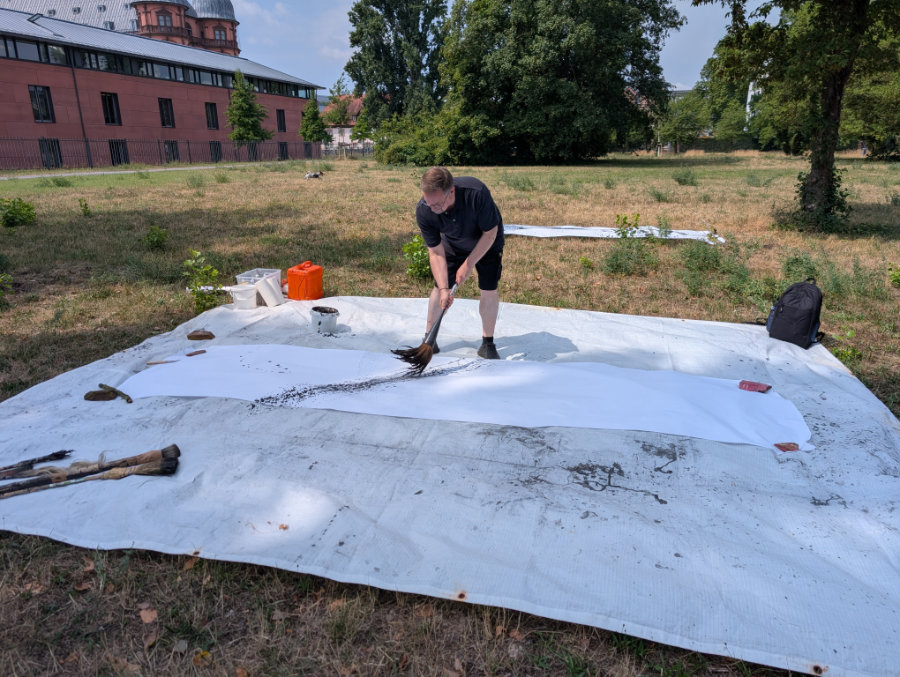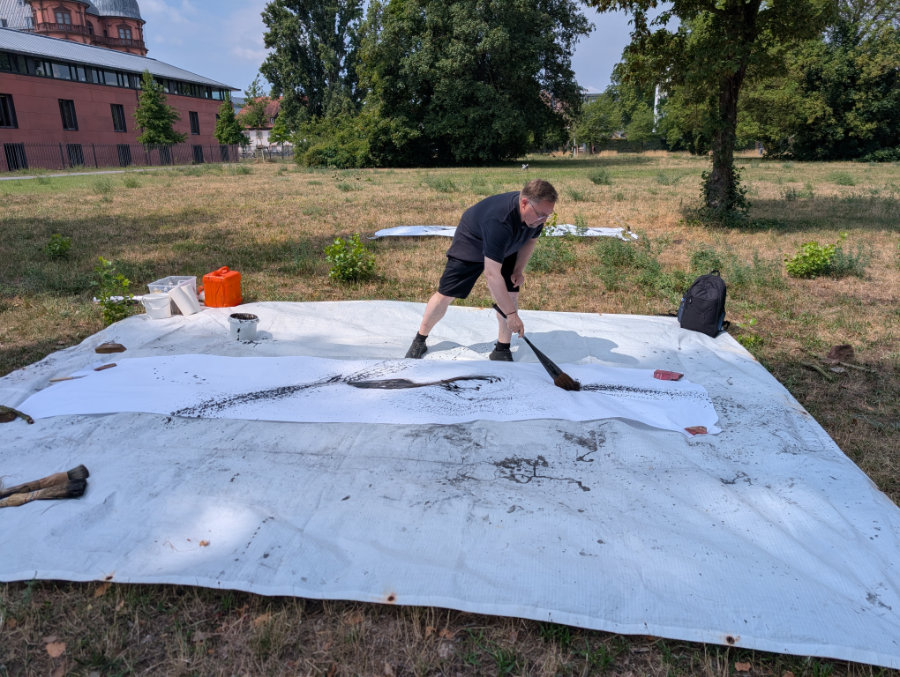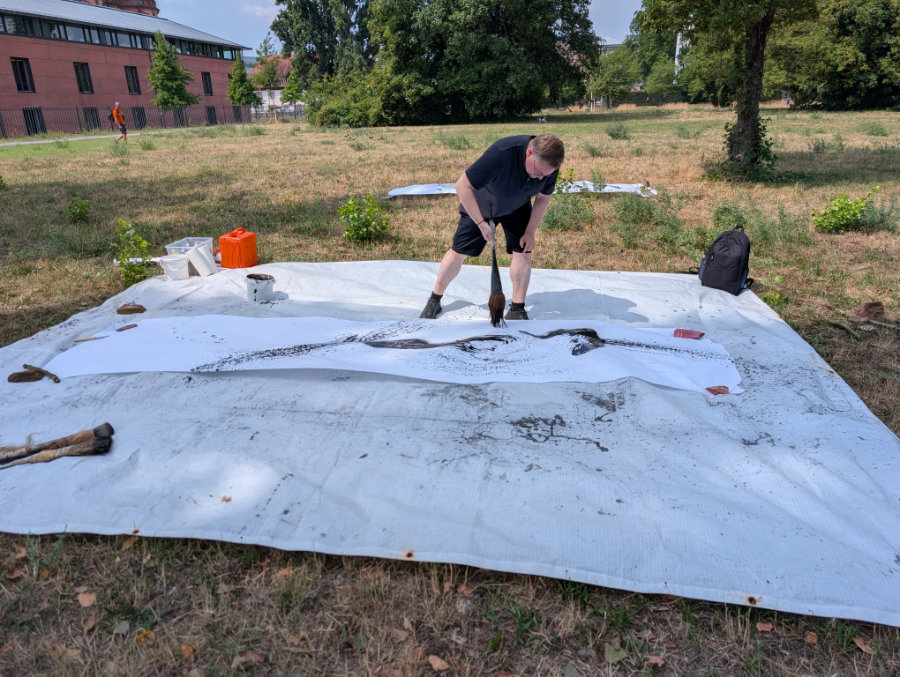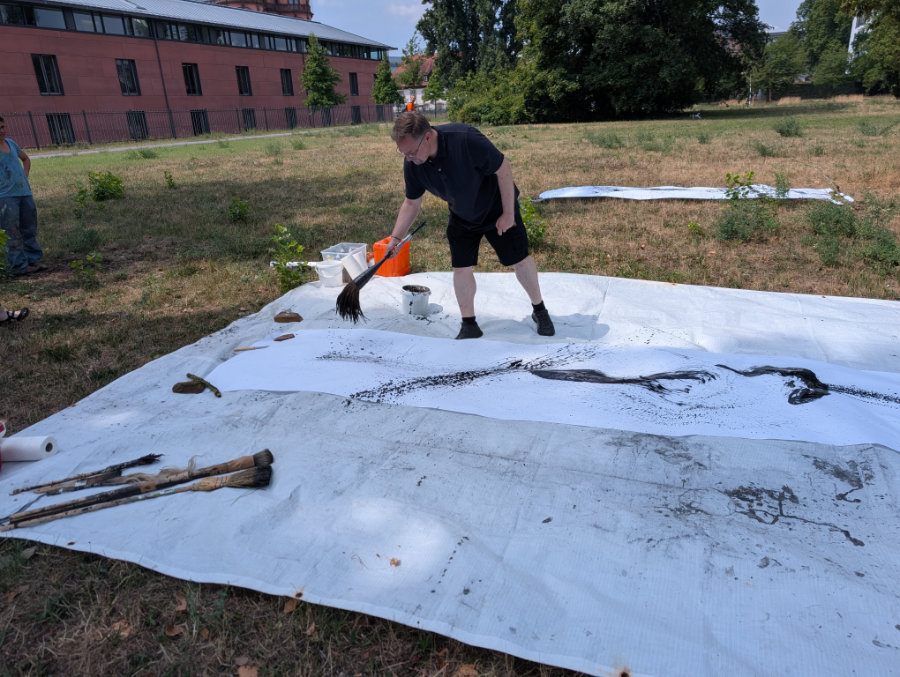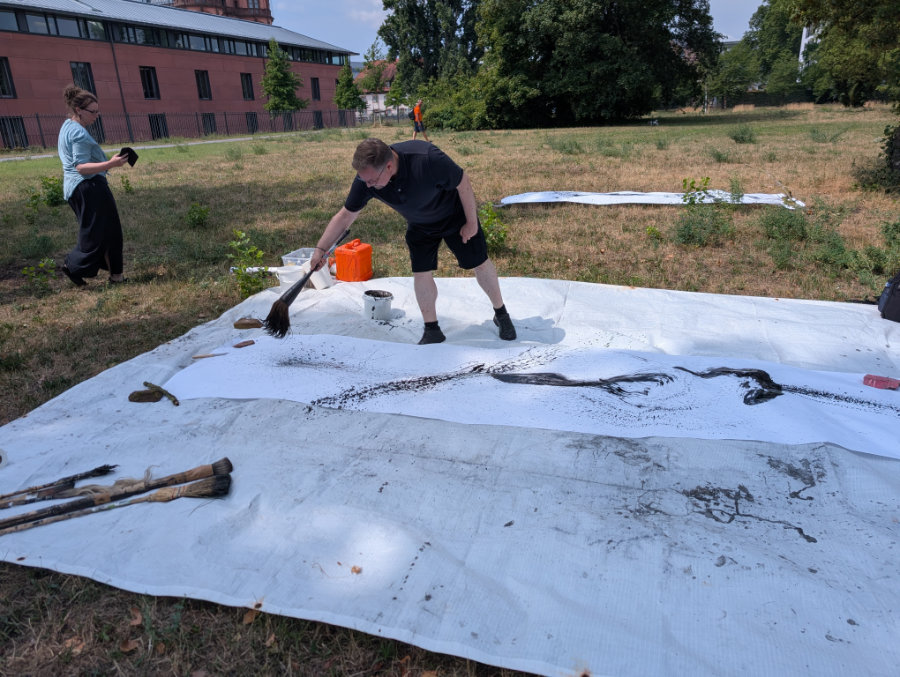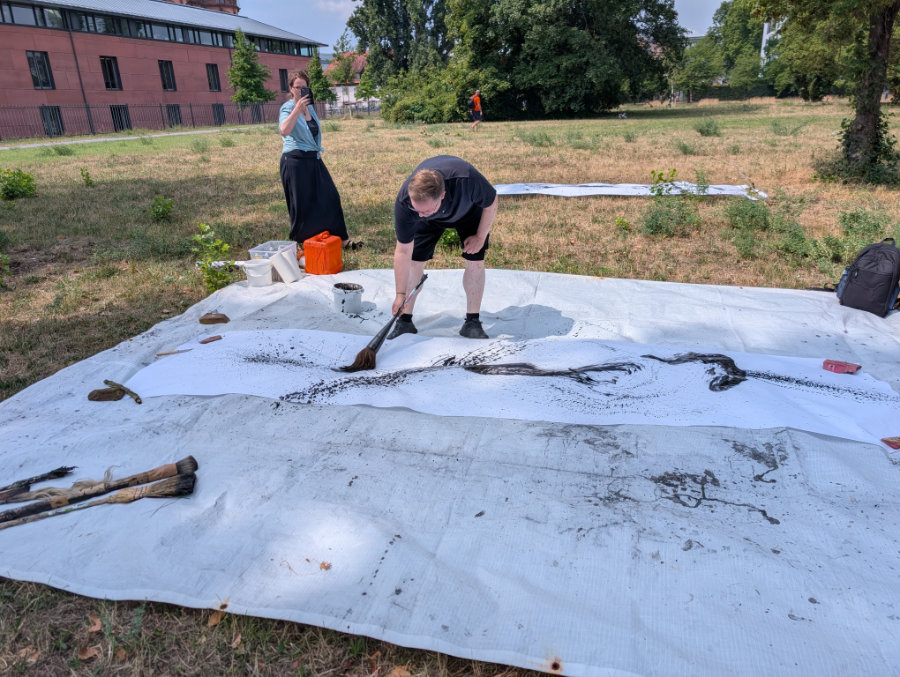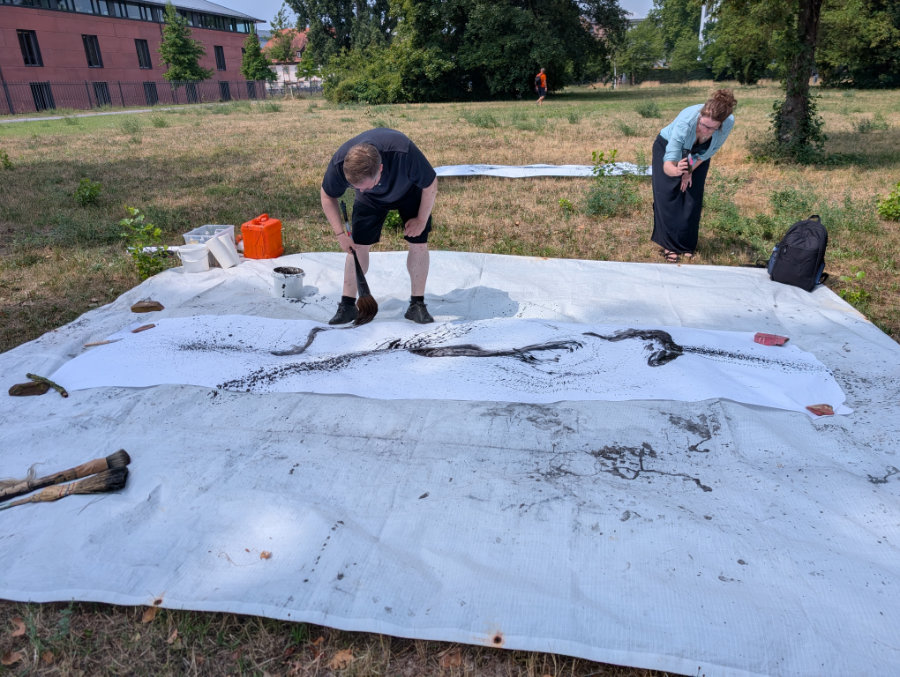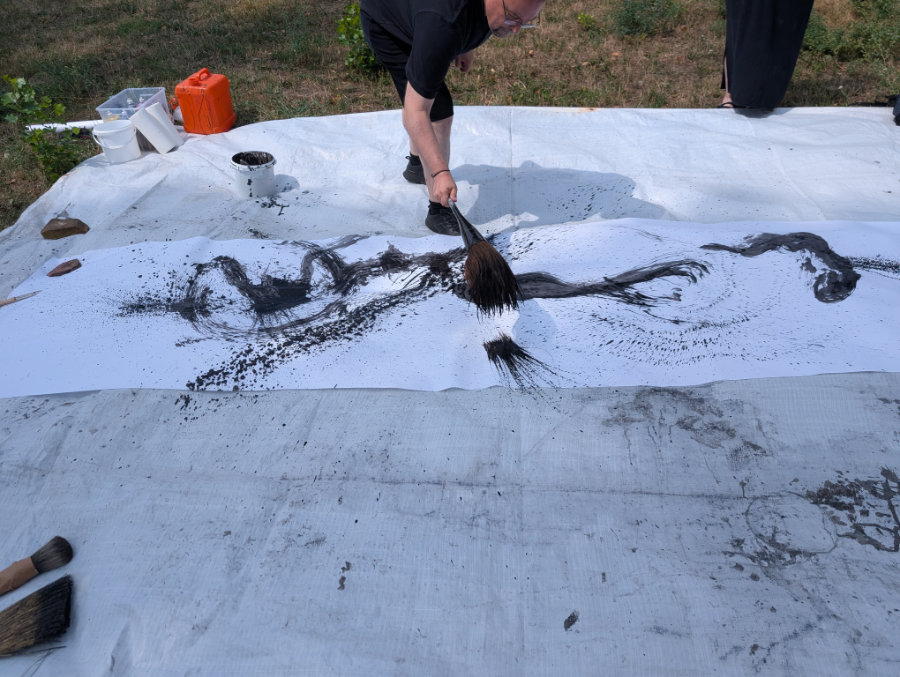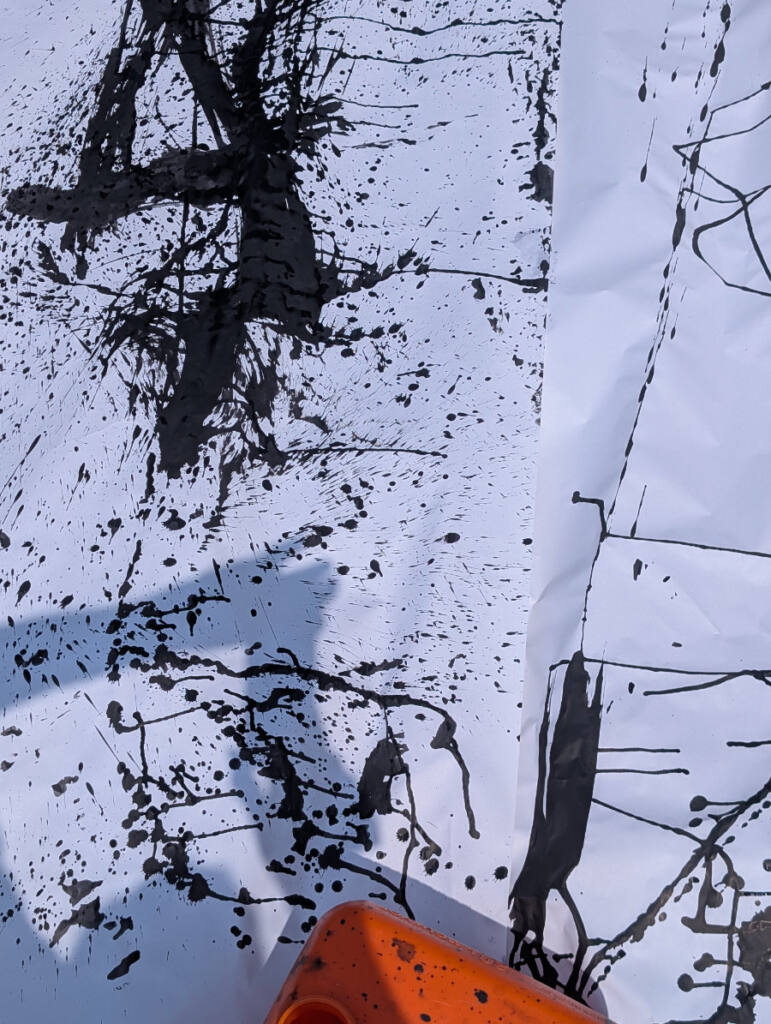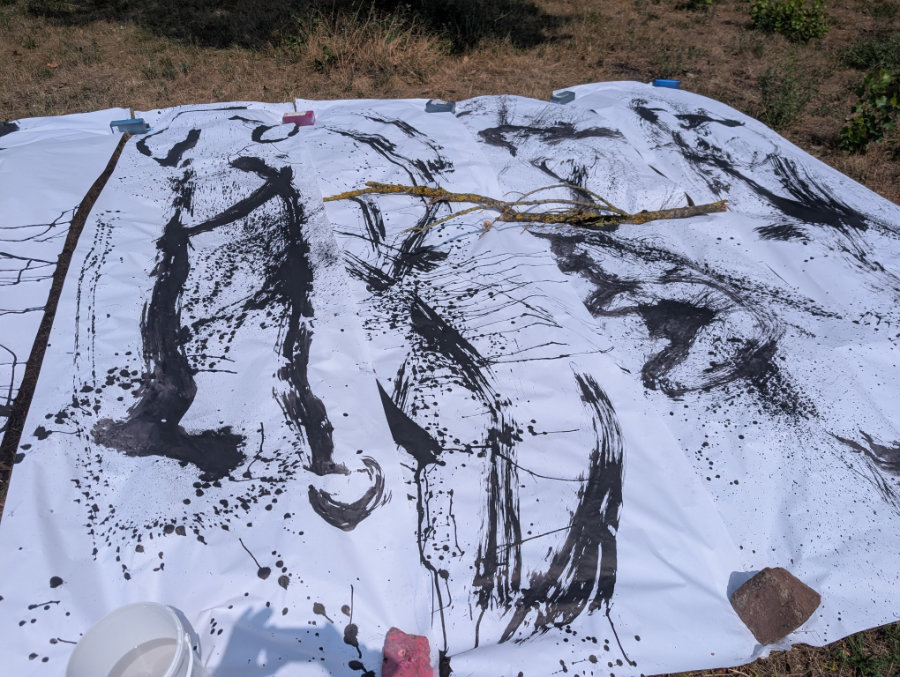
Pinselwurf - Tusche fliegt
Kalligraphie und Performance
Workshop mit Benno Kotterba
Ein großer Topf mit Tusche, ein großer Pinsel, eine große weiße Fläche - und dann mit dem richtigen Schwung, mit Konzentration der Schlag wie ein Peitschenhieb auf und über das Papier. Die Tuschetropfen fliegen, bleiben in der Luft hängen, fallen wie Regen - der Pinsel hat ein Bild auf das Papier geworfen, das diesen Moment voller Dynamik und Energie und die Bewegung von Körper und Hand fixiert. Natürlich bleibt es nicht aus, das auch wir durch die Tusche gezeichnet sind: schwarze Tropfen auf Hand, Gesicht und Kleidung.
Was wir tun
Wir arbeiten mit den Pinselwurfbildern weiter, finden einen Gedanken, ein Gedicht, einen Songtext, den wir kalligraphisch und farbig hineinarbeiten.
Wir arbeiten mit großen Pinseln draußen auf einer Wiese im Park hinter dem Gottesauer Schloss in der Nähe unseres Ateliers. Tusche fliegt auf lange Papierbahnen oder auf große Aquarellbögen. Wenn noch Zeit bleibt entwickeln wir die "Wurfbilder" weiter mit Farbe, Schrift, Grafik, Texten. Je nach Begeisterung schließen wir auch noch einen Folgetag für die Weiterbearbeitung an. Den Tag dafür verabreden wir noch vor Ort.